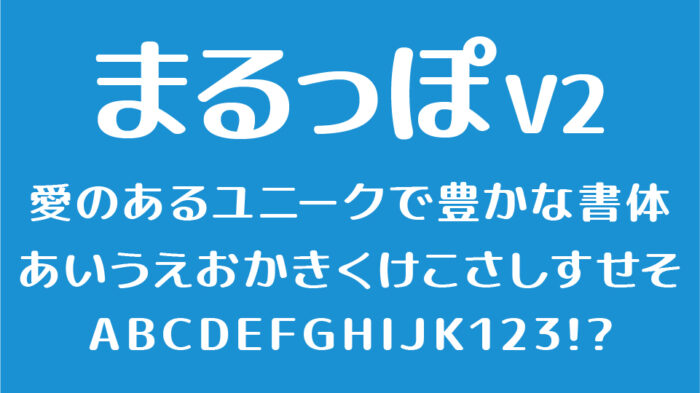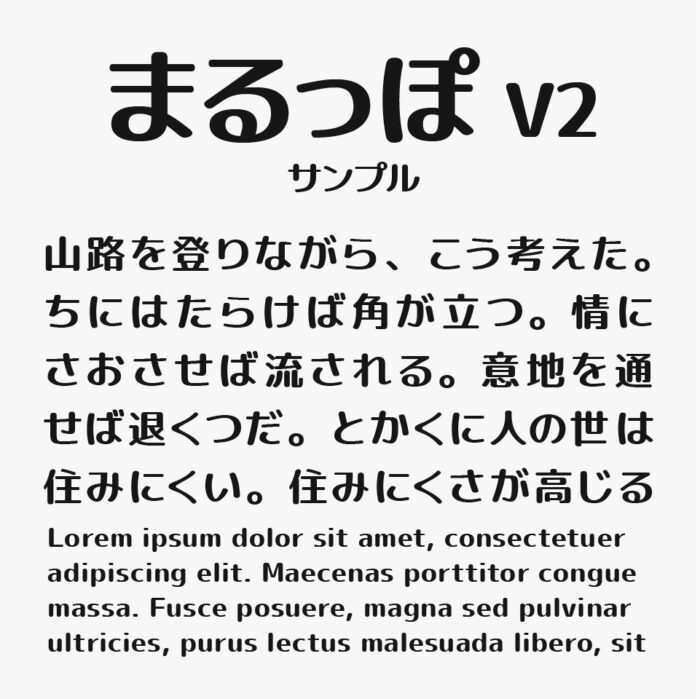
まるっぽフォントV2
まるっぽフォントV2フォントは、MPLUSフォントをベースにタイポス風に変形加工して作成したタイポス系丸ゴシック体です。
縦線の太さと横線の太さに抑揚があり、ふっくらとした丸みが印象的な、やさしく親しみやすいフォントです。見た目に安心感があり、モダンで親しみやすい仕上がりとなっています。